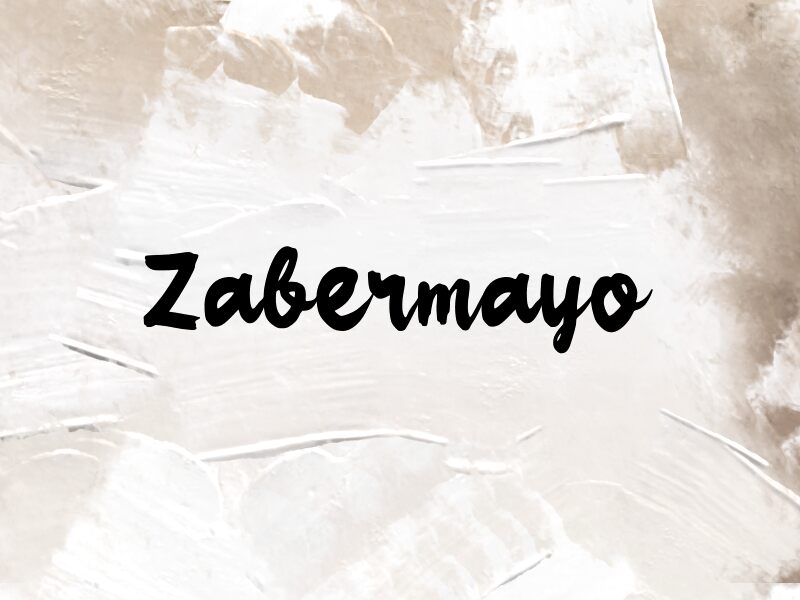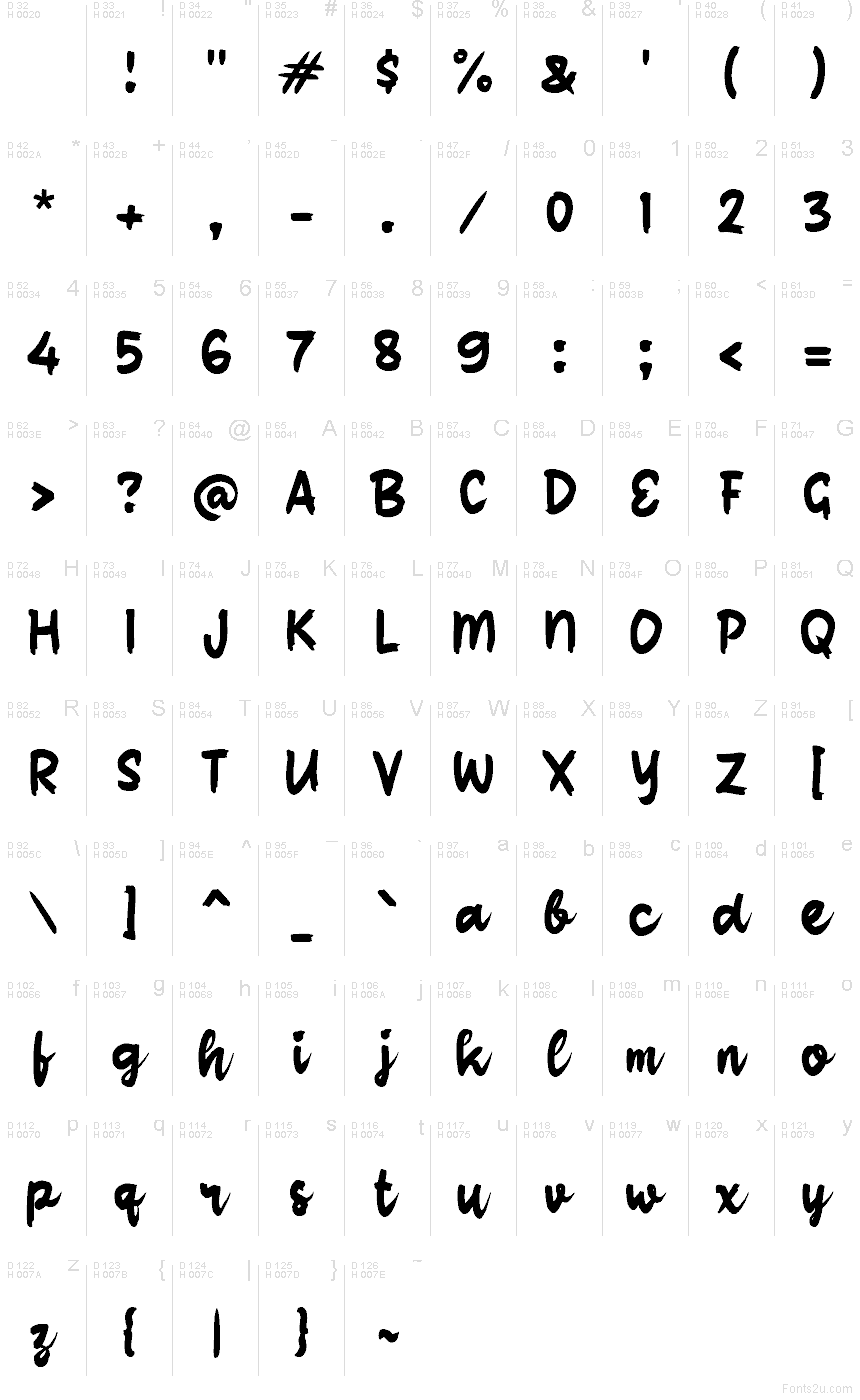
Zabermayo
Zabermayo di Wep è un font gratuito in stile brush script, caratterizzato da un tratto libero e pittorico. Le lettere appaiono ampie e corpose, con tratti spessi, giunture arrotondate e rapidi slanci verso l'alto che mantengono la parola dinamica, senza perdersi nella rigidità della calligrafia classica.
Si adatta perfettamente a branding informali, titoli di poster, copertine di album, packaging per caffetterie e grafiche per i social media, dove un font gratuito deve trasmettere l'autenticità di una scritta fatta di getto. Grazie alla corposità dei tratti e al ritmo incalzante, è ideale anche per loghi brevi, grafiche per merchandise e titoli d'impatto che cercano una voce immediata e pittorica.